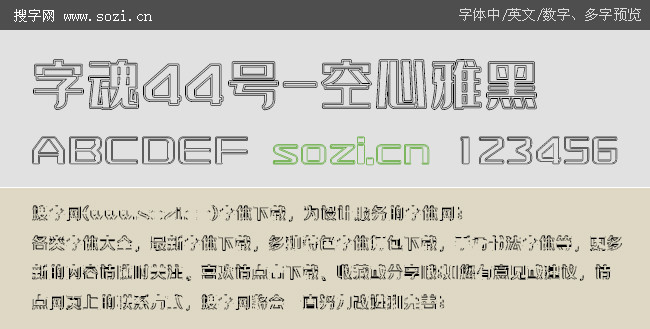
字魂44號-空心雅黑
搜字網(wǎng)提供一款字魂44號-空心雅黑中文字體下載,該字體是一款創(chuàng)意體字體,該字體包含6763個中文、字母、 符號和數(shù)字,具有古典、有力、簡約、中國風 的風格,可以滿足您設計上的各種需求,該字體主要用于圖書、H5、活動展會、雜志、廣告、影視傳媒、青春校園、活動 等場景。